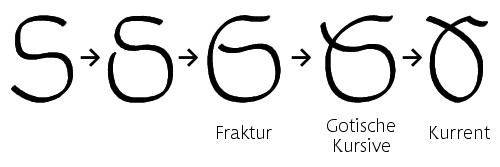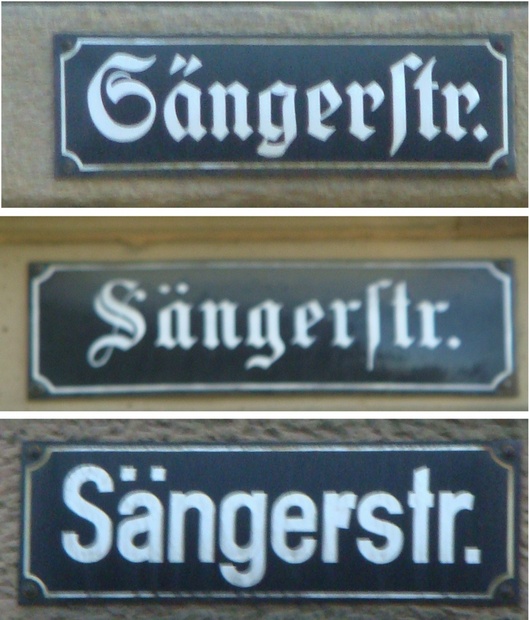
Muss da mal was die "Profis" fragen....
So nach den Demos gegen den Wahnhof in Stuttgart mach ich "Stuttgart-sightseeing" - und da fotografiere ich auch die schönen alten Strassenschilder, sofern vorhanden.
Heute sind mir die drei alle an einer Kreuzung aufgefallen...
Nun, Fraktur erkenne ich noch...aber wer bitte erklärt mir die unterschiedlichen "S" am Wortanfang? Warum, wo angewand, typografisch gut(?), etc. Leider etwas unscharf (aber wer ein Demoplakat tragen muss, kann nicht mehr ordentlich fotografieren....
Der Begriff »Fraktur« hat eine Doppelbedeutung, das ist etwas verwirrend. Einerseits wird er für alle gebrochenen Schriften verwendet, andererseits für eine Teilmenge der gebrochenen. Die zweite Schrift z. B. ist im engeren Sinne eine Gotisch, also keine Fraktur, im weiteren Sinne (des Sammelbegriffs) eben doch eine Fraktur, weil gebrochen.
Ich danke zunächst mal für die Antwort. Nur wünschte ich mir eine irgendwie geartete "Bewertung" der Schriften. Wenn ich als Laie die drei Schilder anschaue, dann erscheint mir beim obersten das "S" einfach zu schwer gegenüber den anderen Buchstaben, bei zweiten Schild ist es gerade andersrum...irgendwie sind beide Worte nicht "ausgewogen"....das dritte erscheint mir "kalt" und nüchtern, distanziert. ich hätte nicht gedacht, dass bei so einem solchen unmitelbaren "Vergleich" solche "gefühlten" Unterschiede so deutlich werden!
nicht nur die Anfangsbuchstaben unterscheiden sich, sondern es handelt sich sogar um drei komplett unterschiedliche Schriften, eine serifenlose und zwei Frakturschriften. Bei den beiden letzten unterscheiden sich nicht nur die Anfangsbuchstaben sondern auch alle übrigen, die darauf folgen. Warum Du drei so verschiedene Schilder auf einem Fleck angetroffen hast? Vermutlich stammen die Schilder aus drei verschiedenen Schildergenerationen. Auch Schilder sind ja Moden unterworfen und im Laufe der Zeit mag es den unterschiedlichen Oberbaudirektoren (oder wer auch immer dafür zuständig ist) gefallen haben, die Schrift auf den Schildern zu ändern/modernisieren. Und da Behörden doch auch sparsam sind, haben sie die noch gut erhaltenen Schilder einfach an Ort und Stelle belassen und nur die beschädigten ausgetauscht – und schon hat man einen hübschen Schildersalat beisammen, der dem aufmerksamen Betrachter etwas über die typografische Geschichte der Stadt verrät.
Ich habe nicht ganz verstanden, was Du nun wissen möchtest. Das S im ersten Beispiel hat die in der Fraktur übliche Form. Auf folgender Abbildung siehst Du, wie diese Form entstanden ist, und wie sich aus ihr schließlich die Form des S in der deutschen Schreibschrift entwickelt hat.
… Nur wünschte ich mir eine irgendwie geartete "Bewertung" der Schriften. Wenn ich als Laie die drei Schilder anschaue, dann erscheint mir beim obersten das "S" einfach zu schwer gegenüber den anderen Buchstaben, bei zweiten Schild ist es gerade andersrum...irgendwie sind beide Worte nicht "ausgewogen"....das dritte erscheint mir "kalt" und nüchtern, distanziert. ich hätte nicht gedacht, dass bei so einem solchen unmitelbaren "Vergleich" solche "gefühlten" Unterschiede so deutlich werden!
Ja, Schriften sind ein ganz wichtiges gestalterisches Ausdrucksmittel – und das sogar im doppelten Sinne. Zunächst haben sie einen ganz konkreten Inhalt, den man über das Lesen erfassen kann. Zusätzlich transportieren Schriften auch noch eine Anmutung. Das kann ein historischer Kontext sein (Straßenschilder in Fraktur verbindet der Betrachter in aller Regel mit vergangenen Zeiten), auf alle Fälle wird zusätzlich ein emotionaler Eindruck vermittelt. Eine Schrift kann sachlich und neutral sein, abweisend wirken, edel und exklusiv rüberkommen oder auch freundlich und einladend. Gute Typografie ist ein enorm wichtiges Stilmittel und will mit Bedacht eingesetzt werden.
Die falsche Schrift am falschen Ort kann völlig verkehrte Signale aussenden. Klassisches Beispiel hierfür wäre die Traueranzeige gesetzt in der Schrift Comic Sans, eine fröhlich-naive, rundliche Schrift, die in diesem Kontext den Eindruck erweckt, die Hinterbliebenen freuten sich über das Ableben des Verstorbenen (was im ein oder anderen Fall tatsächlich so sein mag …).